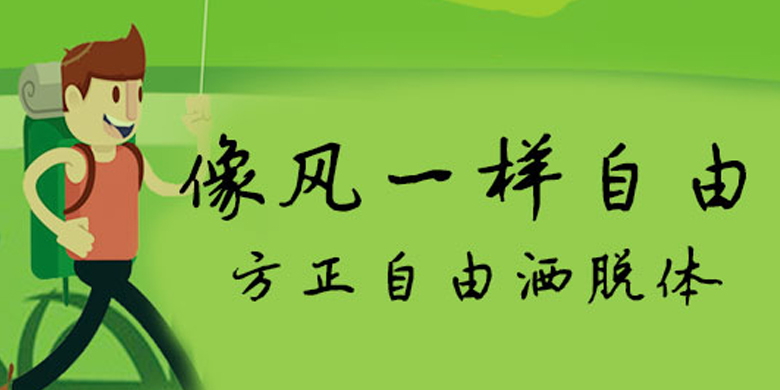
方正手迹-方正自由洒脱体
方正手迹-方正自由洒脱体,这款字体结构工整、笔画清晰,兼顾美观与易读性,适用于标题、正文、海报、包装、LOGO 等多种场景。字形优雅稳定,风格百搭耐看,适配日常排版与创意设计,让文字呈现更舒适、更具质感。方正手迹-方正自由洒脱体一笔一画,皆是细节,以均衡的比例、流畅的线条打造舒适视觉体验,字形端正大气,风格简约现代。无论是商业设计、品牌宣传还是日常排版,都能轻松驾驭,让文字更有格调与力量。方正手迹-方正自由洒脱体字体下载。
这是一款充满力量的字体,笔画线条富于变化,有着行云流水般的写意书风。单字的结构舒展挺拔,排列在一起,有种娓娓道来的感觉,适用于文艺类的书刊、品牌广告和产品包装设计,以及社交网络的个性化用字。